HI THO FONT CHM CHUYN I FONT CHM
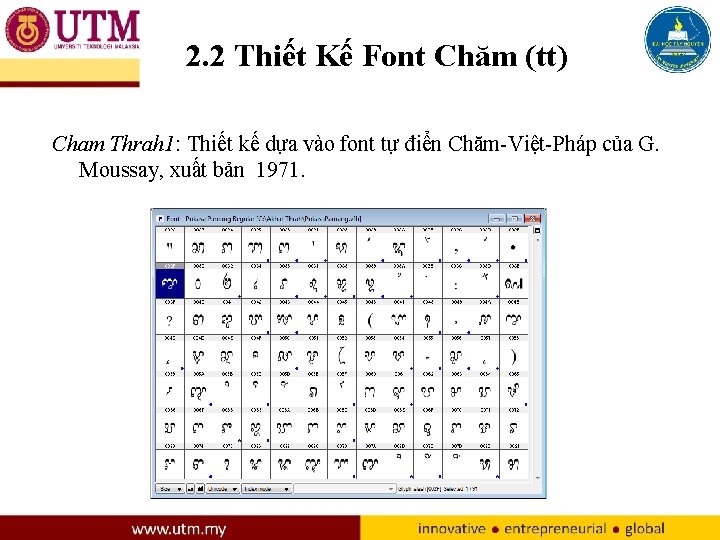
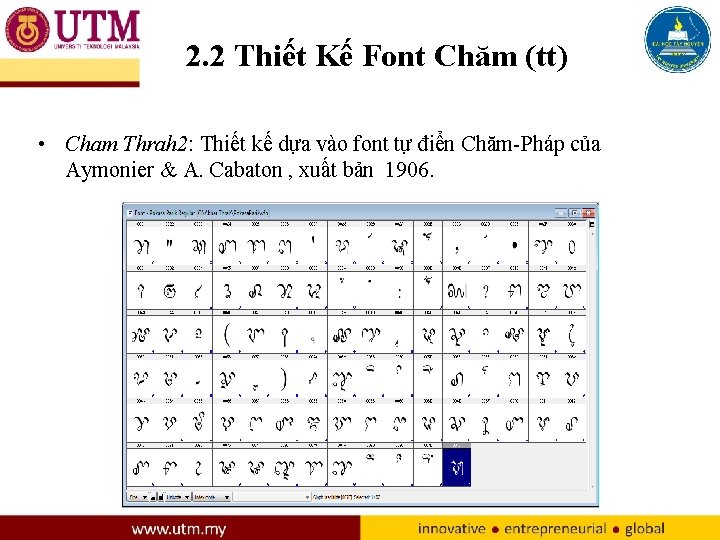
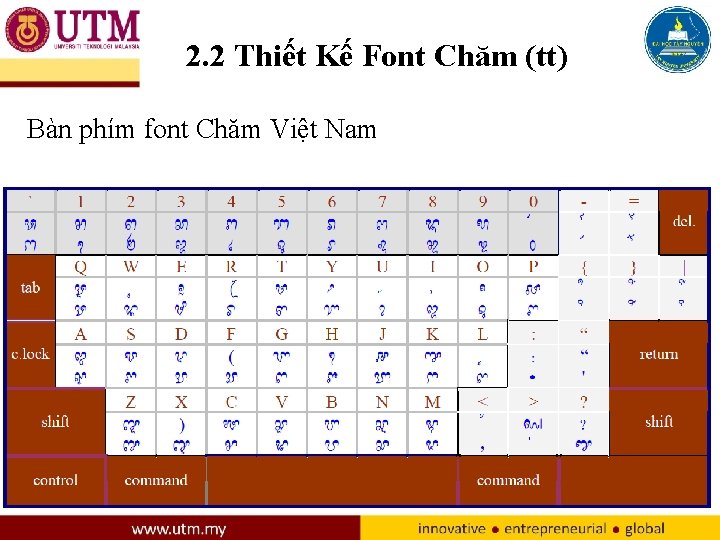
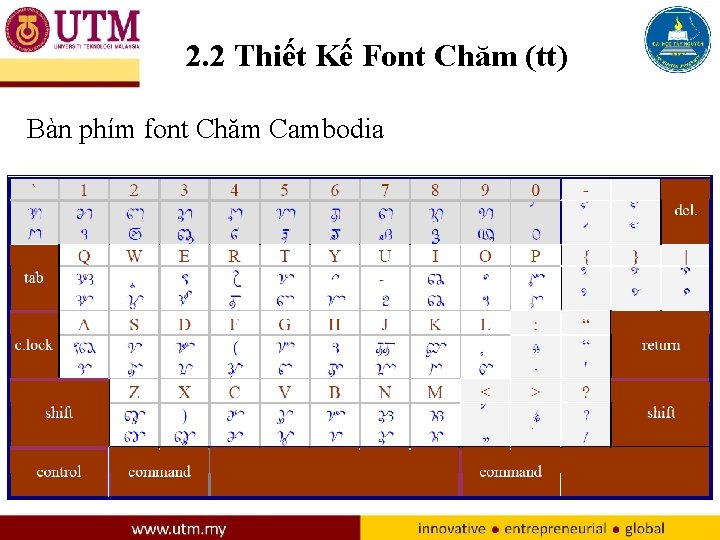
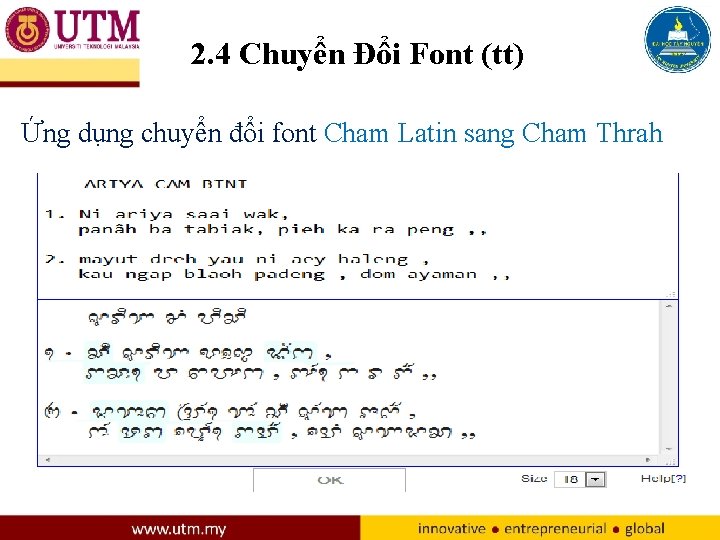
HỘI THẢO FONT CHĂM, CHUYỂN ĐỔI FONT CHĂM VÀ TỰ ĐIỂN ĐIỆN TỬ INFORMATION TECHNOLOGY AND INDIGENOUS LANGUAGE PRESERVATION CASE STUDY IN THE CHAM LANGUAGES IN VIETNAM Người Tbáo cáo: 1. TS. Buôn Krông Tuyết Nhung 2. Ph. D. Văn Ngọc Sáng
1. GIỚI THIỆU - Người Chăm sống tập trung ở Ninh Thuận, Bình Thuận, và một số tỉnh phía Nam. Ngôn ngữ Chăm thuộc gia đình Đa Đảo “autronesian”. - Chữ Chăm cổ xuất hiện từ thế kỷ thứ 2 trên bia ký Võ Cạnh Nha Trang (Filliozat, 1969). - Tiếng Chăm xuất hiện lần đầu tiên trên bia kí Đồng Yên Châu (Trà Kiệu) vào thế kỉ thứ 4. (Coedes, G. , 1939). - Chữ Chăm truyền thống xuất hiện bia ký Po Rome vào thế kỷ thứ 17 (Durand, 1903). - Chữ Chăm cải biên (BBSSCC) được hình thành năm 1978.
1. GIỚI THIỆU (tt) - BBSSCC cải tiến chữ Chăm làm chệch mục tiêu bảo tồn chữ Chăm truyền thống (Han, 2007). - Vì vậy việc nghiên cứu bảo tồn, phát triển chữ Chăm không chỉ có ý nghĩa về mặt lý luận mà còn có ý nghĩa thực tiễn. - CNTT là một giải pháp hữu hiệu nhằm hỗ trợ bảo tồn, phát triển chữ viết và ngôn ngữ Chăm.
2. X Y DỰNG MỘT SỐ ỨNG DỤNG 1. Khảo sát sử dụng chữ viết Chăm 2. Thiết kế font Chăm 3. Thiết kế bàn phím Chăm ảo 4. Chương trình phiên chữ Latin sang Cam Thrah 5. Xây dựng tự điển điện tử Chăm - Việt
2. 2 Thiết Kế Font Chăm • Đã thiết kế 3 font Chăm Thrah cho hệ thống Windows và Macintosh • Đang thiết kế 2 font Chăm Jawi (dùng cho tôn giáo) • Đã đăng tạp chí Scopus (Thiết kế font Cham cho hệ thống Windows và Macintosh)
2. 2 Thiết Kế Font Chăm (tt) Cham Thrah 1: Thiết kế dựa vào font tự điển Chăm-Việt-Pháp của G. Moussay, xuất bản 1971.
2. 2 Thiết Kế Font Chăm (tt) • Cham Thrah 2: Thiết kế dựa vào font tự điển Chăm-Pháp của Aymonier & A. Cabaton , xuất bản 1906.
2. 2 Thiết Kế Font Chăm (tt) • Cham Thrah 3: Thiết kế dựa vào font trên tài liệu Chăm Cambodia đang sử dụng.
2. 2 Thiết Kế Font Chăm (tt) Bàn phím font Chăm Việt Nam
2. 2 Thiết Kế Font Chăm (tt) Bàn phím font Chăm Cambodia
2. 3 Bàn Phím Chăm Ảo
2. 4 Chuyển Đổi Font Ứng dụng chuyển đổi font Cham Latin sang Cham Thrah Bài đăng trên tạp chí Scopus: Technology Applications in Cham Language Conservation
2. 4 Chuyển Đổi Font (tt) Ứng dụng chuyển đổi font Cham Latin sang Cham Thrah
2. 4 Chuyển Đổi Font (tt)
2. 5 Xây Dựng Tự Điển Điện Tử (tt) Xây dựng tự điển điện tử Việt-Chăm; Chăm-Việt Sơ đồ cấu trúc mục từ
2. 5 Xây Dựng Tự Điển Điện Tử (tt) Giao diện chính của tự điển: Việt-Chăm; Chăm-Việt
2. 6 Chương Trình Dạy Ngôn Ngữ Chăm
2. 6 Chương Trình Dạy Ngôn Ngữ Chăm(tt)
2. 7. Tạo nhóm Album Chuyên Đề
3. Kết luận và kiến nghị - Sản phẩm nghiên cứu ứng dụng font Chăm, chuyển đổi font Chăm, tự điển điện tử Chăm Việt là công cụ hỗ trợ tra cứu từ ngữ tiếng Chăm. - Sản phẩm bước đầu ứng dụng công nghệ thông tin vào công tác bảo tồn, gìn giữ, phát triển tiếng nói và chữ viết của người Chăm. - Phần mềm tạo điều kiện thuận lợi cho việc nghiên cứu và giảng dạy tiếng Chăm cho học sinh, sinh viên, cán bộ tại địa phương và các nhà khoa học nghiên cứu văn hóa ngôn ngữ.